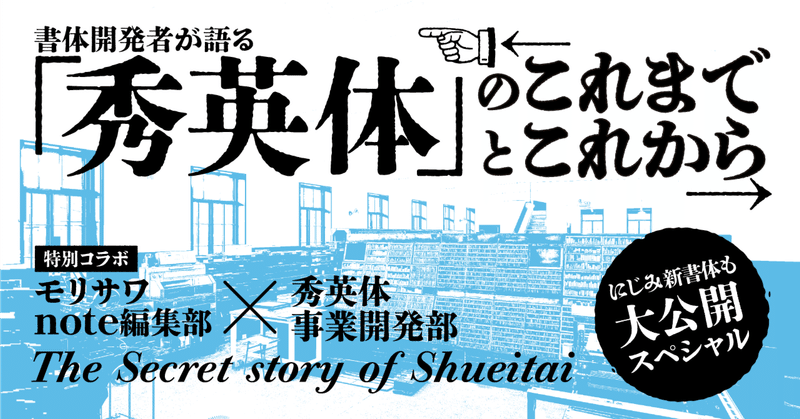
書体開発者が語る「秀英体」のこれまでとこれから〜にじみ新書体も大公開スペシャル〜
明治初期から100年以上にわたり愛され続けてきた「秀英体」の歴史や改刻秘話から、現代のニーズに合わせた新たな取組みまでさまざまなお話を伺いました。モリサワでも以前から秀英体を提供しており、中盤のインタビューでは今年リリース予定の新書体についてもふれているので、ぜひ最後まで読んでみてくださいね。
1.「秀英体」とは?
秀英体は、日本を代表する総合印刷会社「大日本印刷株式会社」(以降、DNP)が独自に開発したオリジナル書体です。広辞苑や新潮社の書籍などに書体が採用されているほか、ポスターやパッケージなどでも使われており、秀英体を詳しく知らなくても無意識に目にしている方も多いと思います。
DNPの前身にあたる「秀英舎」は1876年(明治9年)に創業。まもなく活字の自家鋳造を開始し、秀英体の開発が始まりました。活版印刷の時代からDTP、電子書籍へと文字を巡る環境が大きく移り変わった現代もなお、秀英体は親しまれています。
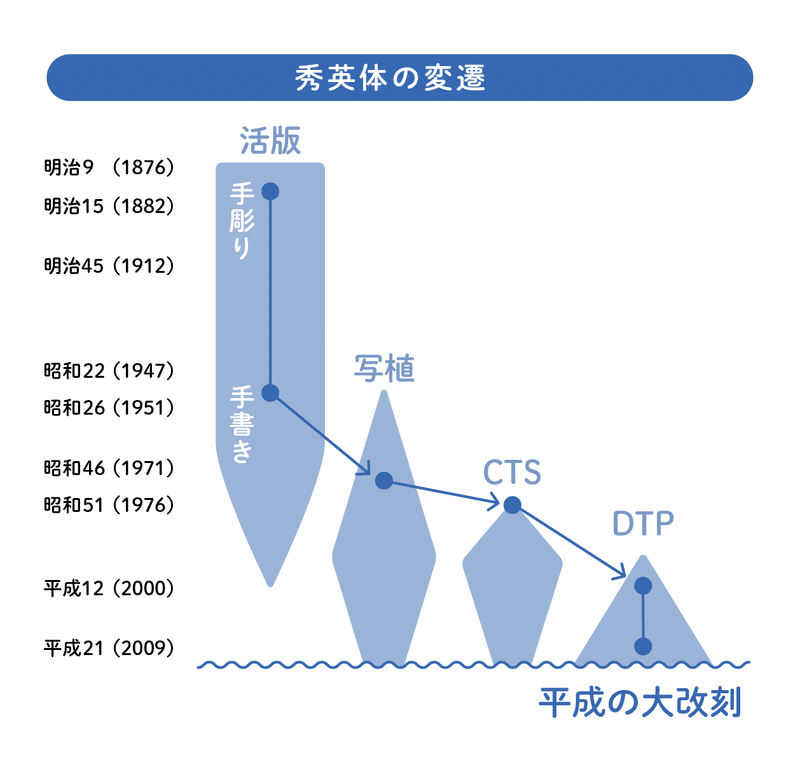
モリサワnote編集部では、これまで自社開発書体を取り上げることが多かったのですが、今回はユーザーの皆様の中でもファンが多い「秀英体」にスポットを当て、その魅力について深掘りしていきます!
2.秀英体の開発者さんに色々聞いてみた!
■お話を聞いた人
大日本印刷株式会社 秀英体事業開発部
・左:伊藤正樹さん(書体:秀英にじみ四号太かな)
・右:宮田愛子さん(書体:秀英にじみ丸ゴシック)
―本⽇はよろしくお願いします。まずはお二人について伺います。どのような経緯で秀英体の部署へ入られたのでしょうか?
伊藤:私は当初違う事業部にいたのですが、DNPには社内人材公募の仕組みがあって、入社して3~4年目の時に秀英体の用途開発の担当者を募集していることを知ったんです。
元々美術大学出身でタイポグラフィの授業があったので秀英体のことも、DNPの活字の歴史も知っていましたし、関心もあったので応募しました。1998年頃から担当しているので秀英体歴としては23~24年になります。
宮田:私は情報系の出身でしたが、目に見えるものを作りたいと思ってDNPに入社しました。当時C&I事業部という部署がありまして、配属された先の部のテーマの一つが秀英体で、伊藤さんがテーマリーダーをされていました。
―そうなんですね!お二人は元々国語が得意とか読書好きとか、以前から文字になじみがあったのでしょうか?
伊藤:実は僕、読書が苦手なんです。あまり普段も本を読まないんですけど、職業柄気になりますね(笑)。
ただ、小さい頃から文字の形は好きでした。地元が関西なんですけど、阪急電車のサインが丸ゴシックで物心ついた時からいいなぁと思っていて。あとは野球が好きなのですが、甲子園球場のスコアボードが手書きの明朝体でかっこいいなぁと思っていました。
宮田:私の場合、小学生の時に初めて入ったクラブがレタリングクラブだったり、大学時代に文字やフォントの形と感性の関係を研究テーマにしていたりと、文字に惹かれるものはあったように思います。
2-1 秀英体のルーツ
―お二人とも書体にご縁があったのですね。早速なのですが、先日秀英体の全文字一覧が載ったポスターを入手したんです!ここに書かれている約2万3千文字、この一文字一文字にお二人が関わっていらっしゃるんですよね?
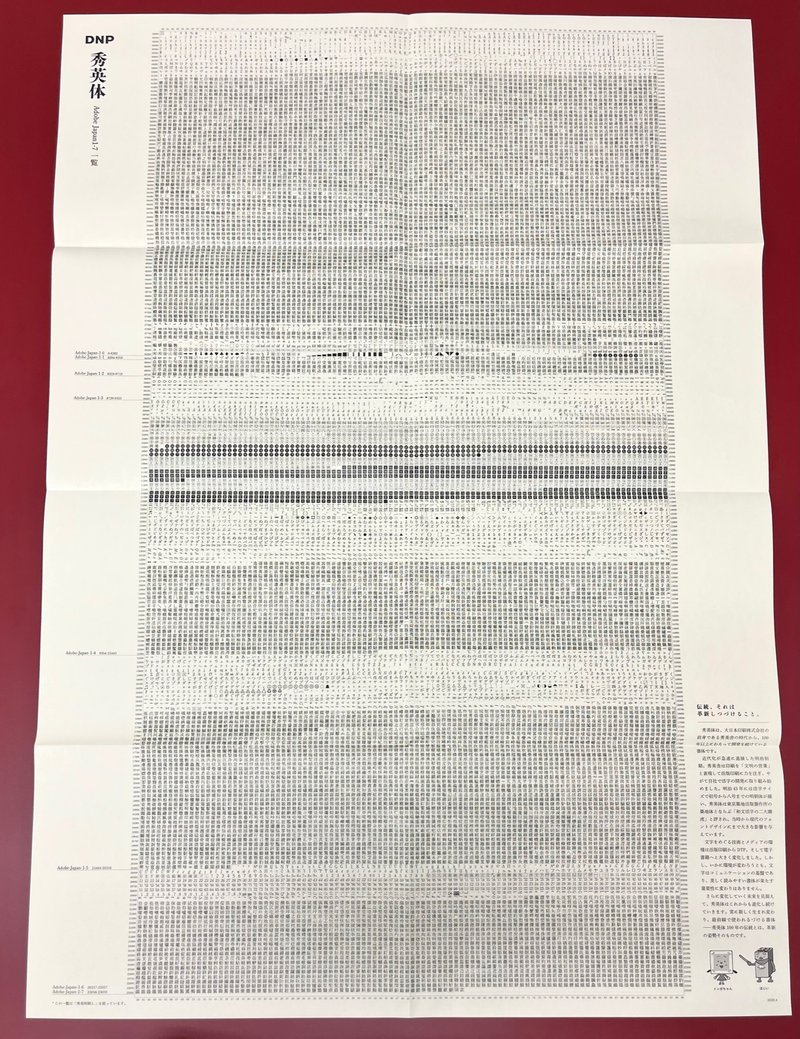
伊藤:はい。一文字一文字、一点一画を見ました。デザインのチェックだけでなく、宮田さんは漢字の、とめ・はね・はらいなどの字形が正しいかどうかをひらすら見てましたよね。
宮田:見てましたね(笑)。「平成の大改刻」以降も、書体を年々増やしていて、秀英体の書体ラインナップは、現在24書体になりました。
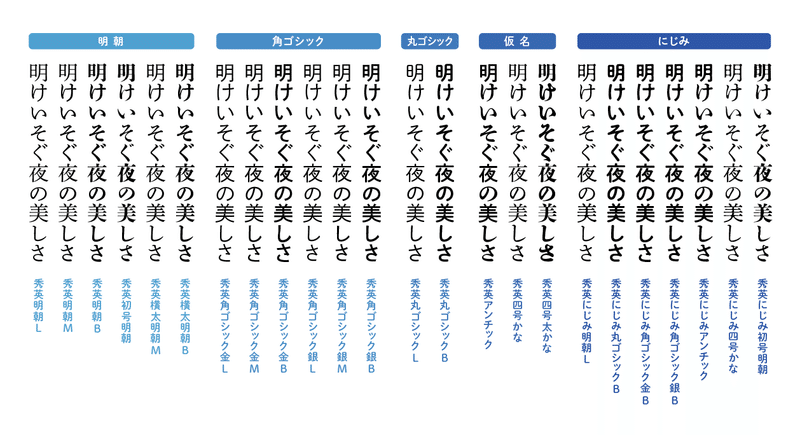
―秀英体のルーツを辿ると活版印刷の時代(明治期)から始まっていますが、当時は金属活字だったんですよね?
宮田:そうですね。今でこそ活字は懐かしさや温かみ、レトロな雰囲気が魅力なんですけど、当時は活字しかなかった時代なので、そもそも印刷するための道具の一つでした。
伊藤:当時は拡大・縮小ができなかったから、見出しは見出しなりの形、本文は本文用の形、初号や一号、二号とサイズによって職人が1文字ずつ彫っていたんです。サイズごとに文字の形を作っていたことと、その活字にインクをつけて紙に押し当てていたことが、アナログで印刷していた時代の魅力なのかなと思います。
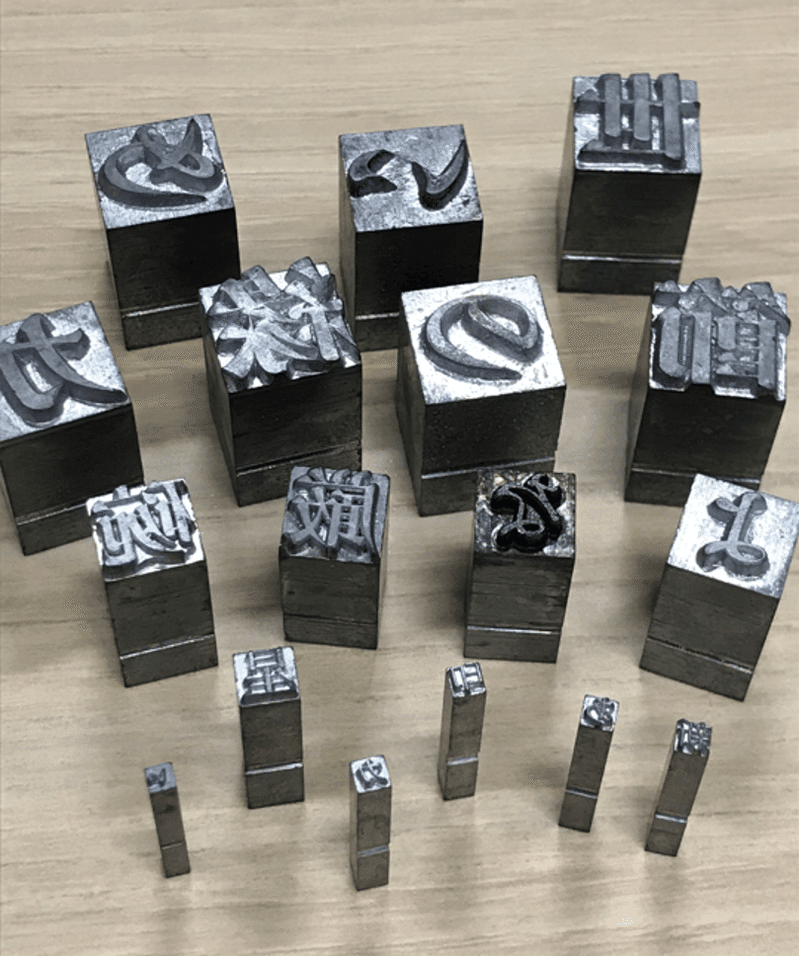
2-2 一大プロジェクト「平成の大改刻」
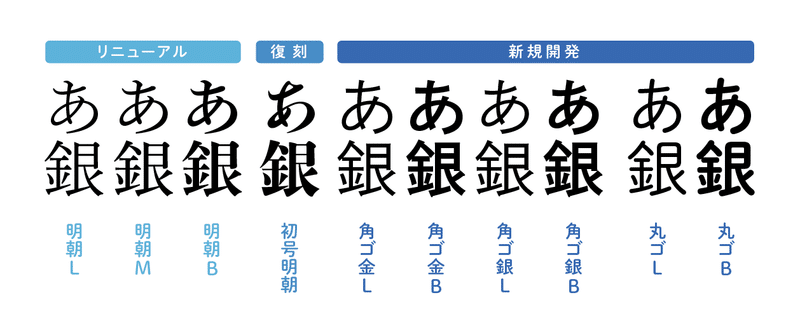
■平成の大改刻
新時代の利用環境に対応するため、2005年(平成17年)からスタートしたプロジェクト。DNP、朗文堂、字游工房、リョービイマジクスからなる開発プロジェクトチームを結成し、7年かけて10書体12万字もの書体リニューアルを行った。
―秀英体の歴史を語るうえで、リニューアルプロジェクトである「平成の大改刻」は欠かせないですよね。中心メンバーとしてお二人も関わっていらしたそうですが、膨大な数の文字を改刻する日々で正直辛くなることはありませんでしたか?
伊藤:その当時は辛さを感じなかったです。それよりも文字を生み出せる喜びの方が強かったですね。宮田さんはもしかしたら辛かったかも(笑)。
宮田:いえいえ(笑)。その時はモリサワさんから秀英体を販売する準備も並行して進めていたので、単に文字を作っているだけの苦しみというよりは、それをたくさんの方に使ってもらえるんだっていう嬉しさが勝っていました。
伊藤:それまで秀英体はDNPの工場内でしか使わない書体だったので、工場で出力するためのメンテナンスはしても、デジタルフォントとして一般販売できるような開発はしていなかったんです。
秀英体もモリサワフォントみたいに世の中に届けられたらいいのにな…とずっと思っていました。ですから、モリサワさんとの連携でそれが叶う喜び、楽しみな部分とドキドキする部分、そういう期待と不安が合わさった感じでしたね。
―平成の大改刻プロジェクトで一番苦労された点、意識された点はどこでしょうか?
伊藤:コンセプトや設計はDNPで行い、監修に朗文堂さん、アウトラインデータの制作は字游工房さんやリョービイマジクスさんに協力して頂いて進めました。それぞれに複数の方が携わっていらしたので、みんなの意見を束ねないといけない。僕らも初めてで不勉強な部分がありましたが、わかるようになってくるとこうしたい!という思いがありましたし、各担当会社さんにも思いがあって、それを調整するのが難しくもあり、楽しくもありました。
―書体の修正のみならず、デジタル化や新書体開発も同時に行われていたんですよね?
宮田:はい。オープン化するにあたって、OpenTypeフォントフォーマットへの対応が必要だったり、アウトラインデータ制作をお願いしていた2社のデータ形式が異なっていたので、フォントファイルにするまでの変換フローをどうするか検討したり。開発と一言で言っても、ただ十何万字作りましたっていうだけじゃなかったことを今思い出しました(笑)。
―途方もない作業の連続だったと思いますが、開発の皆さんの文字に懸ける情熱が伝わってきました。元は社内でしか使用されていなかった秀英体が広く認知されるようになったのも、皆さんの努力があったからこそですね。
宮田:書体の開発はもちろんですが、モリサワさんが「MORISAWA PASSPORT」を展開してくださっていたおかげで、一度にたくさんのお客様の手元に秀英体フォントをお届けすることができるようになったので、とても感謝しています。
―ありがとうございます!続いて、近年リリースされている「にじみ」シリーズについて伺いたいのですが、いつどのような経緯でデジタル化に至ったのでしょうか?
伊藤:「にじみ」シリーズは、2013年に企画書1枚から始まりました。改刻をする時にこれまでの秀英体を振り返る機会がたくさんあって、明治の秀英体、大正・昭和の秀英体を見て、これからの100年に使える書体を見極めていったんですけど、過去の秀英体にはアナログならではの魅力があったんです。インクがにじんだ書物を見て、これをデジタルフォントで再現できないかなと思ったのがきっかけでした。
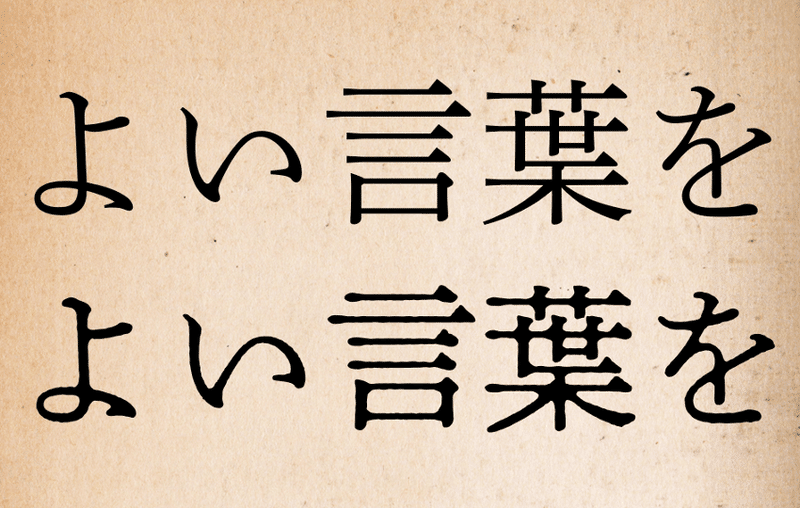
伊藤:平成の大改刻できれいにした秀英体を壊すようなアプローチではあるのですが、活版で刷られた印字物をルーペで見て、どこがどうにじんでいるのか特徴を洗い出し、画像処理ができる社員ににじみ加工を行うプログラムの開発を依頼しました。
書体に詳しい方からは秀英体の評価は高いのですが、詳しくない方やデザイナー以外の方にも秀英体の魅力を感じてほしいと思ったんです。「新しいファンを作る」みたいな。にじみ書体を知ったことで「あぁ、これの元は秀英体なんだ」という入り口を作りたかったのもあります。
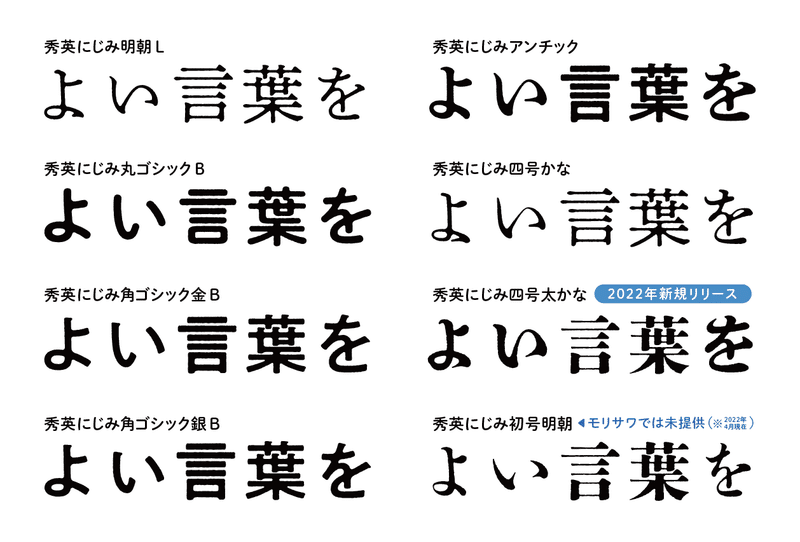
―私もにじみシリーズの独特な風合いが好きです。これをデジタルで表現しているのが素晴らしいですね。
伊藤:こちらの提案を受けてモリサワさんが思い切って世に出してくださったのはありがたかったのですが、実は少しビビってたんですよ(笑)。もちろん僕らはいいと思っていましたけど、何人かのデザイナーさんに事前にヒアリングした際、意見が半々に分かれていたこともあって、批判されるんじゃないかって。
宮田:にじみをデジタルフォントで再現することで、Webや電子書籍でも、活版印刷のようなアナログ感を表現できるのではと考えていたので、それまでのDTPや印刷に携わるユーザーの皆様にお見せするのは不安な面がありましたね。
最初は2016年にWebフォントのサービスに提供して反応をみていたのですが、その後にMORISAWA PASSPORTでも提供できるというお話になってドキドキでした。
伊藤:今では「にじみシリーズ好きです!」と言ってもらえることも多くあるので、やりたいことは間違っていなかったのかなと思います。
2-3 「秀英にじみ四号太かな」「秀英四号太かな+」が新規リリース!
―ここで、記事を読んでいる皆さまだけに新情報です!今年はモリサワから「秀英にじみ四号太かな」と「秀英四号太かな+」をリリース予定です。そこで、これらの書体のベースとなった「秀英四号太かな」について詳しく伺っていきたいと思います。
宮田:平成の大改刻が終わってから、にじみ書体の開発と並行して検討していたのが “かな書体の復刻” で、そのうちの一つが「秀英四号太かな」です。
下段は、漢字の組み合わせ推奨書体
宮田:平成の大改刻では、秀英角ゴシック金・秀英角ゴシック銀・秀英丸ゴシックは共にL・Bの2ウエイトを開発して、リリースしました。その後『秀英明朝はL・M・Bと3つのウエイトがあるのに、なぜ角ゴシックはL・Bしかないの?』『本文用に秀英角ゴシック Mくらいの太さが欲しい』というお声をいただいて、角ゴシックのウエイト拡充をしました。
今まで「秀英といえば明朝」というイメージだったのが、改刻でのゴシック系の拡充によって、より幅広い場面で使っていただけるようになったんです。
宮田:秀英体の可能性は広がって、多くの人に知ってもらえた。じゃあ次は歴史ある秀英体の良さも伝えていきたいよね、という思いから、代々広辞苑の見出しで使っていただいている「アンチック」や、秀英明朝のルーツである「四号かな」の復刻をすることまではすぐに決まりました。
―四号太かなは最後に制作が決まったんですね。
宮田:そうですね。明治や大正の頃に作成された活字見本帳を見ると、普通のひらがなの見本の隣に “太かな” というゾーンがあります。デジタルフォントでウエイト展開というと、単純に同じ骨格で太らせるイメージですが、ここには全然違うすごい形のひらがながあったんですよ。
宮田:おそらく、今だと強調する時に明朝の中に角ゴシックを入れたりするのと同じ感覚で、当時骨格の違う書体を当てていたのかなぁという印象があって。また、昔の絵本を見ると、角ゴシックの漢字と組み合わせて太かなが使われている例があるんです。昔の使われ方をデジタルフォントで再現するというか、そんなフォントデザインを提供できたら面白いねということになりました。
伊藤:太かなは筆の流れの特徴もつかんでいて、現代人が思い浮かばないような個性のあるデザインなんですよね。それが結果的に強調されて見えて、目を引くのかなと思います。うねった書体で他の号数活字の三号、四号、五号とそれぞれ太かながついていて、それぞれの中での強調の役割をなしていた書体だと思いました。
宮田:当時、既に復刻を決めていた四号かなに合わせて「四号太かな」を復刻することにしました。普通のかなデザインと太かながあることを昔の歴史や当時のコンセプトと共に紹介できたらなと思っていたので、良い機会でした。
伊藤:そんな四号太かななんですが、今年モリサワさんからリリースされるのは、元々かな書体だった「秀英四号太かな」に初号の漢字を組み合わせて総合書体とした「秀英四号太かな+」と、これににじみ加工を施した「秀英にじみ四号太かな」になります。
宮田:復刻した他のかな書体についても、かなに漢字を組み合わせた “総合書体” として、モリサワさんから「秀英アンチック+」「秀英四号かな+」をリリースしています。今まではユーザーの皆様のお手元で漢字と組み合わせていた手間がなくなって、より使いやすくなっているので、ぜひダウンロードしてみてください!
―ありがとうございます!今年リリースの太かなシリーズは、どんなシーンで活用してほしいですか?
※残念ながらここではお見せできませんが、商品のパッケージやテレビ番組のタイトル、お店のチラシなどお二人が見つけたさまざまな活用事例を紹介していただきました。
伊藤:これまでの事例を見ると、お笑い系が強いみたいです。伝統的なお店や居酒屋のメニューや広告での利用は想定していたんですけど、びっくりでしたね。お笑い芸人のYouTubeのサムネイルとか、映像の中のテロップにも結構使われているんですよ。
宮田:字幕系だと秀英初号よりも四号太かなくらいの太さとインパクトが合うんだろうなって。1文字でも目立つので、数文字使われているだけで「あ、いる!」っていう(笑)。
伊藤:特徴があるのに字面が大きくて正方形なんですよね。だから使いやすいのかな。初号って平たい文字とか縦長の字とかベタに組むと空間が空き気味でツメ組みが基本になることが多いんですが、四号太かなは癖があるのに四角いので使いやすい。
―確かに!街で四号太かなを見つけたら嬉しくなってしまいそうです。ちなみに、お二人が好きな文字はありますか?
宮田:「な」とかいいですよね。独特な筆のつながり方をしています。
伊藤:「な」いいですね〜。独特の形というと、ひらがなの「ぎ」がすごい形をしていて。一回「うなぎ」で使われていたのを見たことがあるんですけど、歯ぎしりしているような食いしばってるような「ぎ」なんですよ。あと「も」もすごいんですよね。横線が突き出してないっていう…。
(書体:秀英にじみ四号太かな)
―老舗のおいしいうなぎ!が出てきそうです(笑)。書体の話をもっと伺いたいところですが、次の話題に移りましょう。
2-4 活版印刷の歴史を今に伝える「本と活字館」
長きにわたり、日本の書籍や雑誌を製造してきた大日本印刷の市谷工場。その象徴として「時計台」の愛称で親しまれてきた建物を1926年(大正15年)竣工当時の姿に復元し、2020年(令和2年)に誕生したのが本づくりの文化施設「市谷の杜 本と活字館」です(DNP市谷加賀町ビルの隣にあります)。活版印刷の歴史や印刷工程の案内、秀英体に関する展示などを見ることができます。
本や文字が好きな人にはぜひ一度訪れていただきたい……!
―「本と活字館」の見どころを教えてください。
宮田:自分たちで言うのも変ですが、見どころはすべてです!2階で開催している企画展示もおすすめです。本と活字館はVRで館内をまわることもできます。企画展示のアーカイブも含まれているので、昨年開催した秀英体の企画展もぜひ見てみてください。
伊藤:活字館の中では、活字が並んでいる様子や組版の様子も見られますし、ワークショップもあります。あと館内のサインがいいんですよ。壁から大きな活字が飛び出していて、初号明朝で “一階” とか “二階” って書いてあったり。そうした細部まで見ていただきたいです。
宮田:あと秀英推しでいうと、2階に秀英体の活字ベンチがあるので、活字に座るという体験をしていただければ(笑)。
―あっ活字ベンチ座りました!なかなか貴重な経験でした……
宮田:それと、今年リリースする「秀英四号太かな+」は「秀英初号明朝」の漢字を組み合わせているのですが、この “秀英初号明朝の見本帳の復刻版” が2階の購買コーナーで販売されています。手に取って見本帳を毎日眺められるようになりますよ!
伊藤:寝る前などにぜひ読んでほしいですね(笑)。
―いい夢が見られそうです!!本と活字館では「四号太かな」の活字は見られますか?
伊藤:実は四号太かなは見られません…。四号は母型(※)も残っていなくて、見本帳のみです。唯一、号数系で残っているのが初号ですね。明治から使っていた母型が残っていて、初号の母型とそれに鋳込んで作られた40ポイントの活字は見られますが、三号も四号も五号も残念ながらないんです。
でも、活字はたくさん見ることができるので、ぜひご来館ください。
※母型:活字の鋳造のために作成する型のこと。
これがなかなか難しくて面白いんです!
2-5 これからの秀英体と新たな取組み
―現在DNPさんでは “感情表現フォントシステム” という取組みを始めていらっしゃるそうですね。詳しく教えてください。
宮田:改刻や拡充によって、フォントの提供はある程度デザイナーさんをはじめユーザーの皆様にアプローチできたと思いますが、次のステップとして普段私たちが暮らしている中にあふれている書体を楽しんでもらいたいという思いから、この取組みが始まりました。
宮田:文字を読む側が自分で選ばなくても、テキストの内容に応じて自動でフォントが切り替わることで、合うフォントを知ったり体感したりしてもらえればと思って始めたんです。チャットやメールなどコミュニケーションツールで使っていただこうと2018年に発表しました。
その反響として放送局さんからお声掛けをいただいたんです。放送字幕の表示で使用できれば聴覚障害の方にも内容の感情的な部分が伝わりやすくなるんじゃないか、ということで。実用化にはまだクリアしなければならない壁があるので、展開に向けて今検討しているところです。
伊藤:感情表現フォント以外の取組みで言うと、「ディスレクシア」という文字の読み書きが苦手な方が人口の数パーセントいらして、そういう障害のある方たちにとって読みやすいフォントの研究開発を進めています。
伊藤:元々改刻では明治由来の伝統書体を現代に伝えるために、デザイナーさんのニーズを叶える形で進めてきましたが、そもそもDNPが秀英体を開発してきたのは美しい紙面を作ることはもちろん、情報を伝えるという目的がありました。
万人が読みやすい文字もそうですが、読む方やシーンに合わせた文字をシステムと含めて提供できるような取組みをしたい。その一つが感情フォントであり、障害のある方にも読み取りやすい文字の開発です。後者はモリサワさんもたくさん手掛けていらっしゃって実用化まで進めておられるので、今度ご相談できたら嬉しいですね。
―時代のニーズに合わせて進化していく秀英体の取組みに、これからも注目したいと思います。最後の質問となりますが、お二人にとって秀英体とは?
伊藤:「DNPの誇り」です。それを継続して後世に残していく。これからも豊かな文字を作っていきたいと思います。
宮田:伊藤さんは入社前から秀英体を知っていたそうですが、私はそうではなかったので、大日本印刷に入って出会ったものです。今も仕事を続けられているのは秀英体のおかげかもしれないと思うと、秀英体は「なくてはならないもの」ですかね。すみません、いいまとめになってないかも(笑)。
秀英体を今後ともよろしくお願いします!
―今日は貴重な機会と素敵なお話をありがとうございました!
3.あとがき
筆者はモリサワ社内で秀英体を担当していて、かれこれ3年目になりました。街を歩けば自社書体よりも先に秀英体を見つけてしまうほど、目に焼き付いていて大好きな書体の1つになりました。
特に四号太かなはその愛くるしさが魅力的で…モリサワから「秀英にじみ四号太かな」をリリースできることを楽しみにしていたので、今回お話を聞けて個人的にはとてもアツかったです。
次の機会があれば、初号のお話を聞く記事や秀英体の見分け方記事なども書いてみたいな…と妄想は膨らむばかりなのですが、初号に関しては今回インタビューを受けてくださった伊藤さんがひたすら初号の見本帳を眺めていらっしゃるYouTube動画がございますので、そちらもぜひご覧ください。
他にもトークイベントのアーカイブ動画などがアップされており、掘れば掘るほど面白く、とっても “沼” な内容でおすすめです。